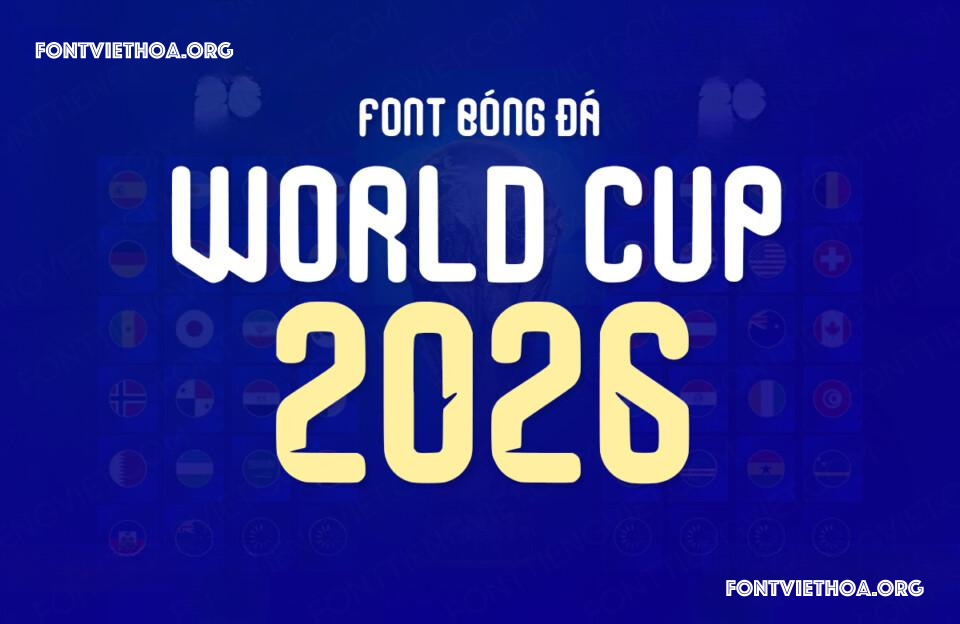
Tên font: Font Việt hoá VIP Adidas WC 2026 – Font Việt hoá World Cup 2026
Tác giả: marfagraphic
Font Việt hoá VIP Adidas WC 2026 là một font chữ đẹp và cứng cáp dành cho World Cup 2026. Với thiết kế độc đáo và hiện đại, font này sẽ giúp bạn thể hiện sự phong cách và chuyên nghiệp trong công việc thiết kế. Font này được thiết kế đặc biệt cho mùa World Cup 2026, với các đường nét và hình dạng thể hiện tinh thần của giải đấu bóng đá lớn nhất hành tinh.
Font này có nhiều tính năng đặc biệt, bao gồm: